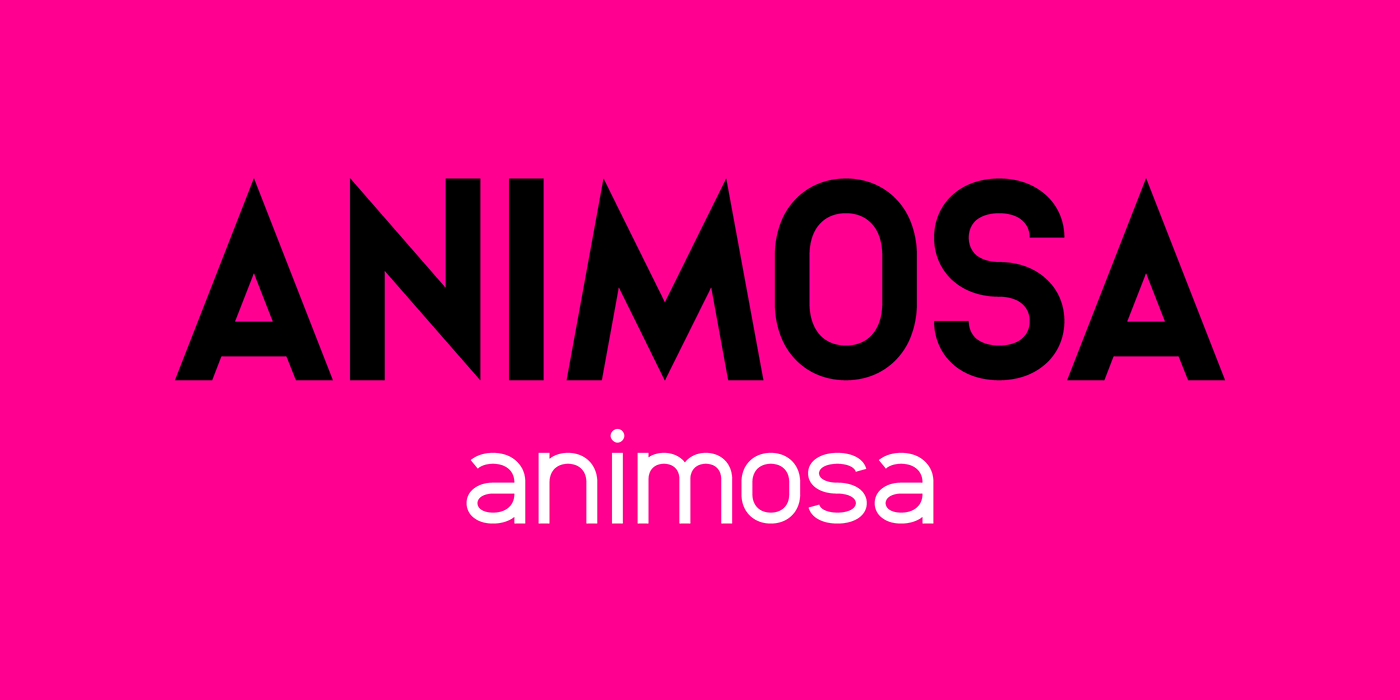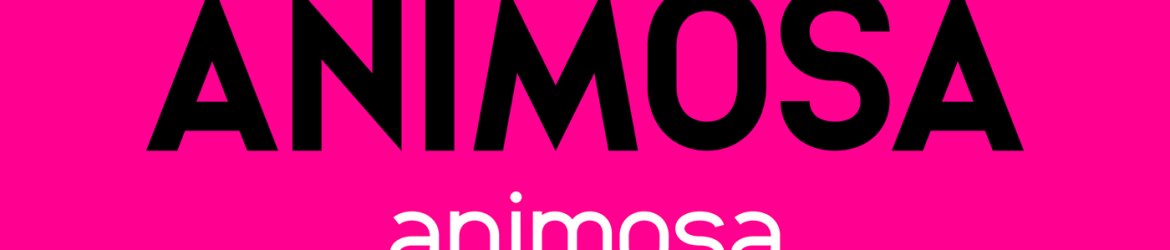
Aqui está uma versão em português do Brasil da descrição solicitada para a página de download da font ‘Animosa Font Family’: A animação suave e elegante da Animosa é perfeita para seus projetos de identidade visual. Esta família de fontes, criada pelo designer Hamilton, oferece uma experiência rápida e envolvente para designers atentos à estética. Seu estilo limpo e minimalista combina com qualquer projeto – seja um logo sofisticado ou uma publicação online. Animosa se destaca por ser um tipo sans-serif perfeito para marcações e logotipos, sua simplicidade e beleza de linhas fazem dela a escolha ideal para textos de citação. Além disso, é uma fonte versátil que funciona muito bem em diversos formatos de mídia, como cartões de visita, revistas, websites ou até mesmo no design gráfico de livros impressos. A família Animosa está repleta de vida e temperamento sofisticado, o que a torna perfeita para aqueles projetos onde a estética tem um papel crucial. É fácil usar em diferentes contextos e combina-se bem em todos os elementos do seu projeto de identidade visual. Então, se você busca uma fonte de estilos simples e elegante para sua próxima campanha ou projeto, o tipo Animosa é uma escolha ótima que certamente não deixará seus clientes faltando por mais um detalhe.